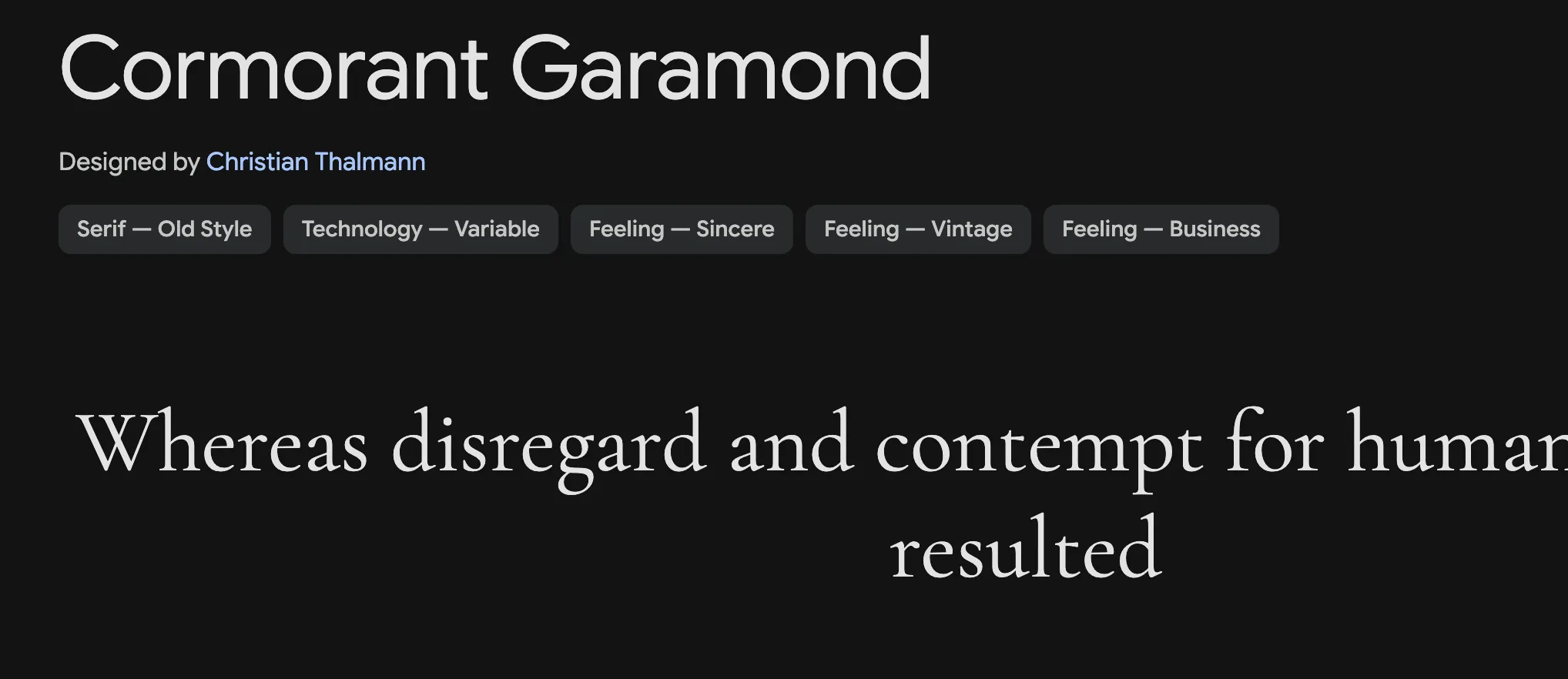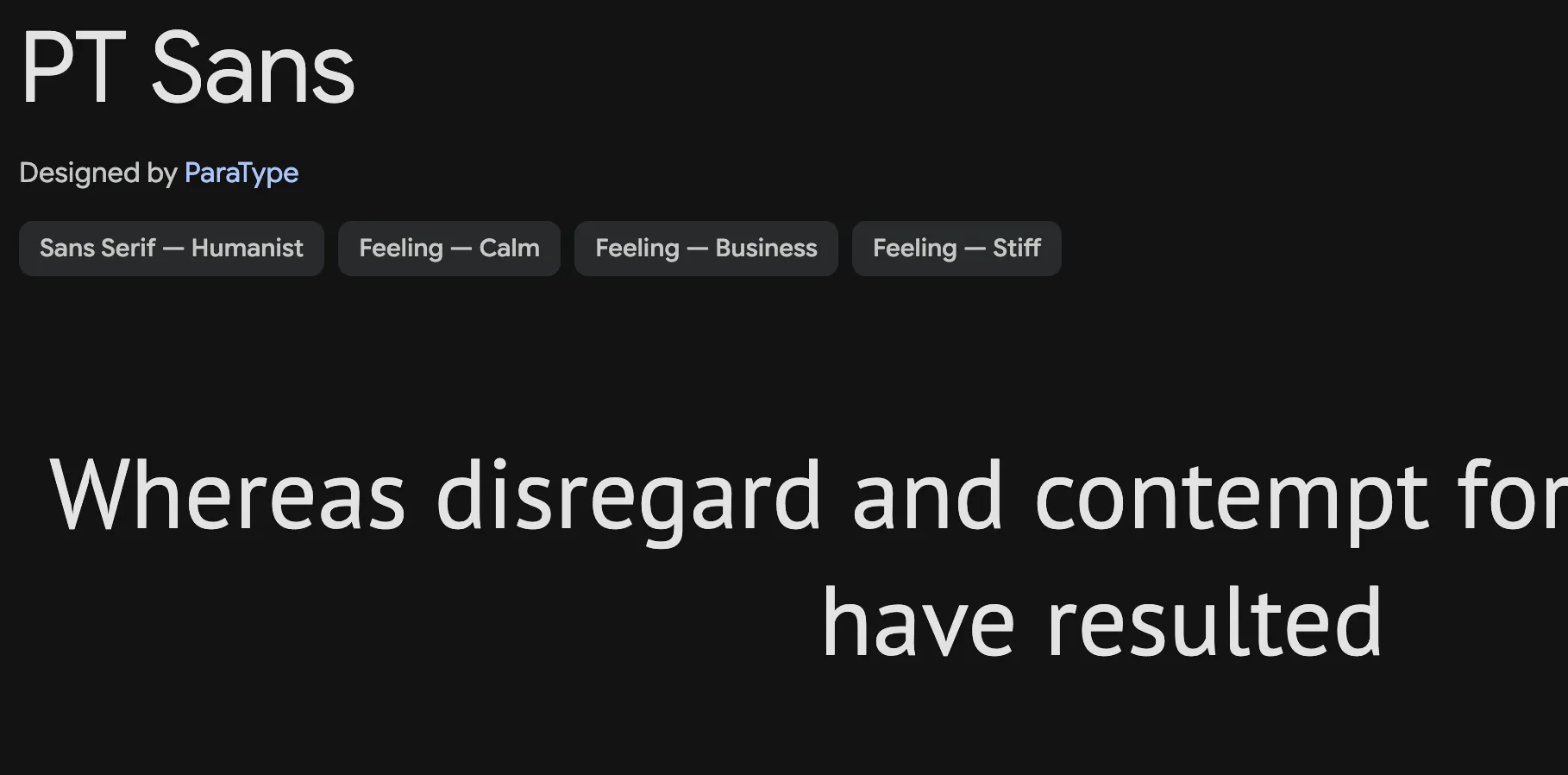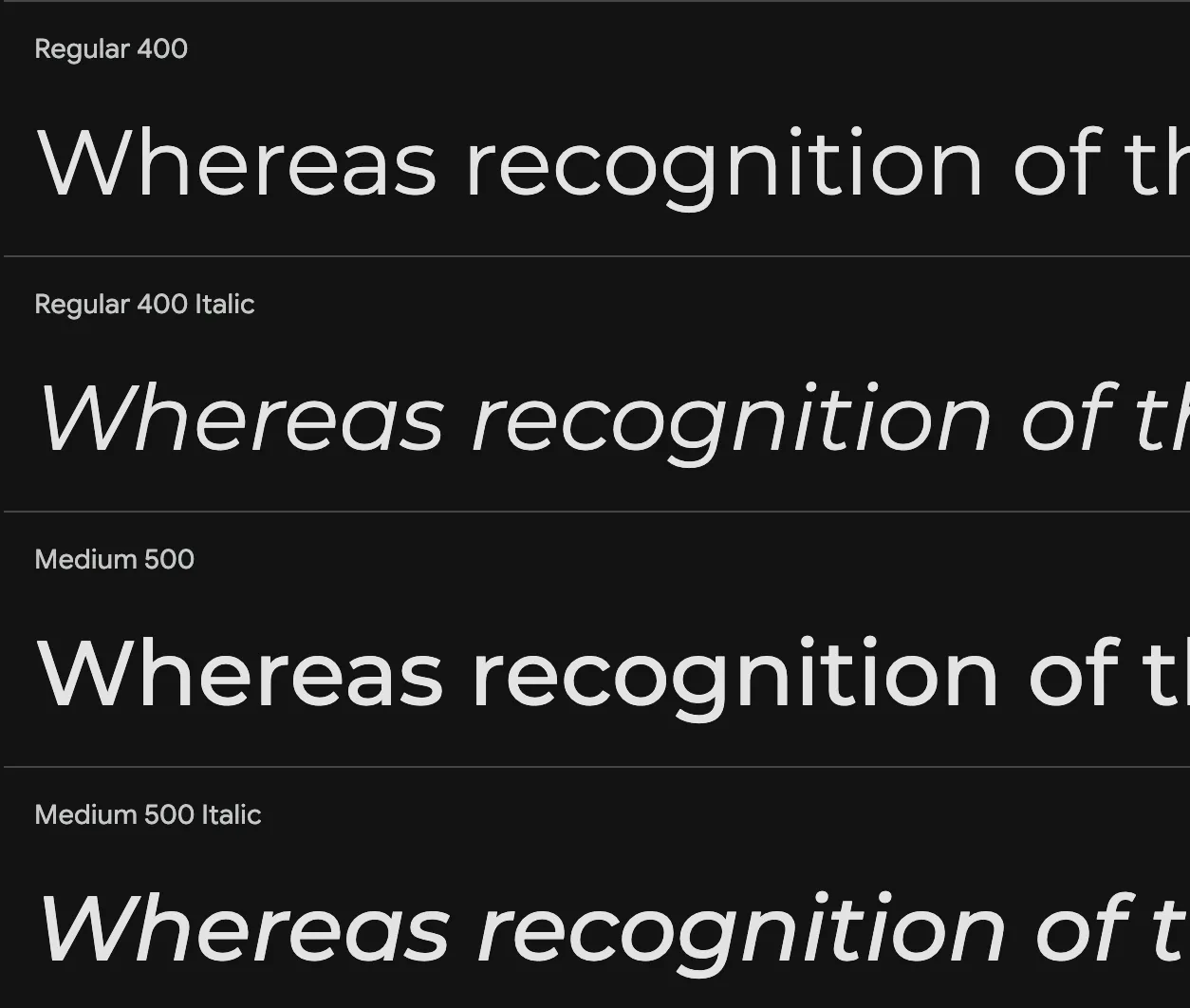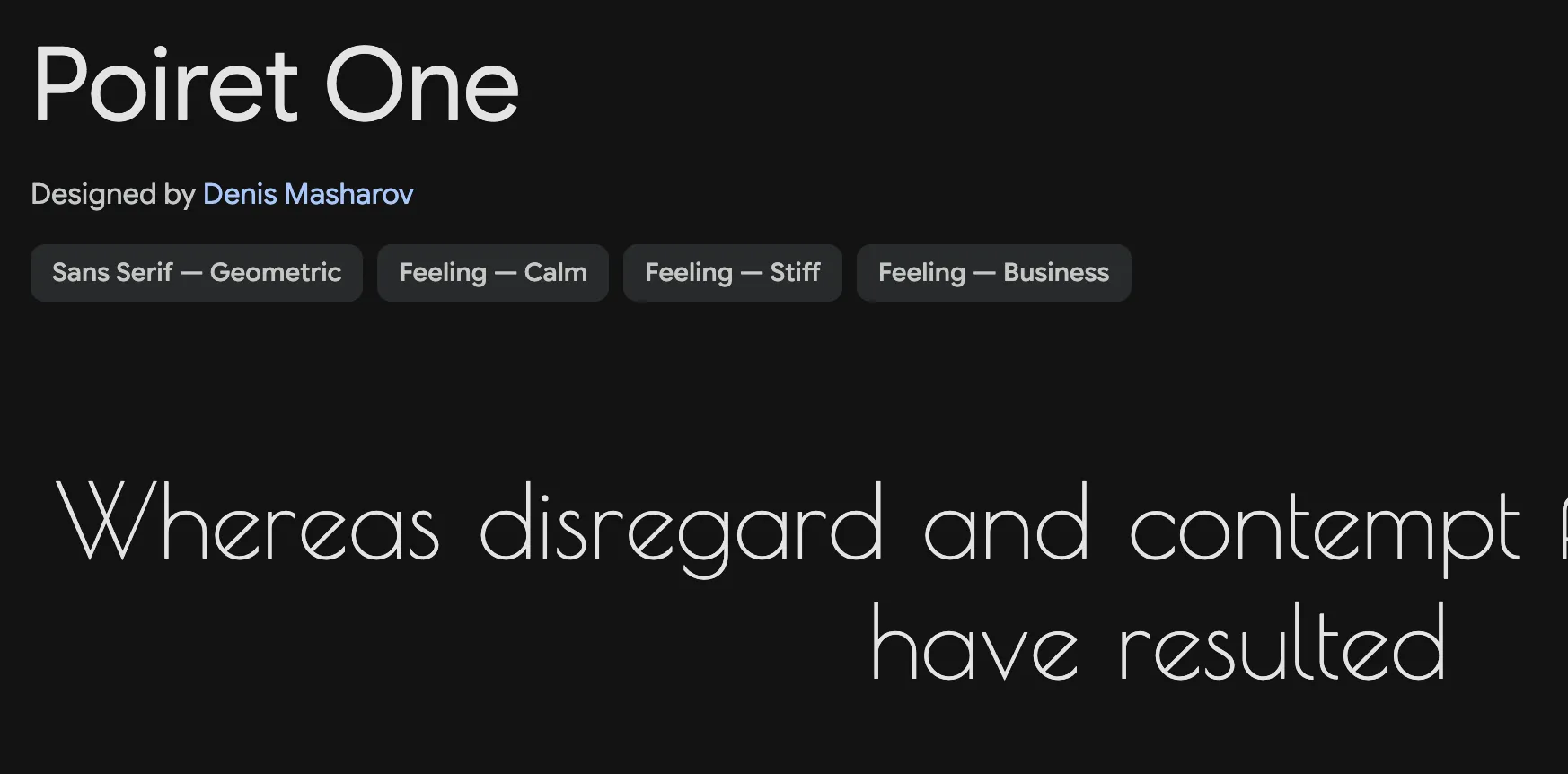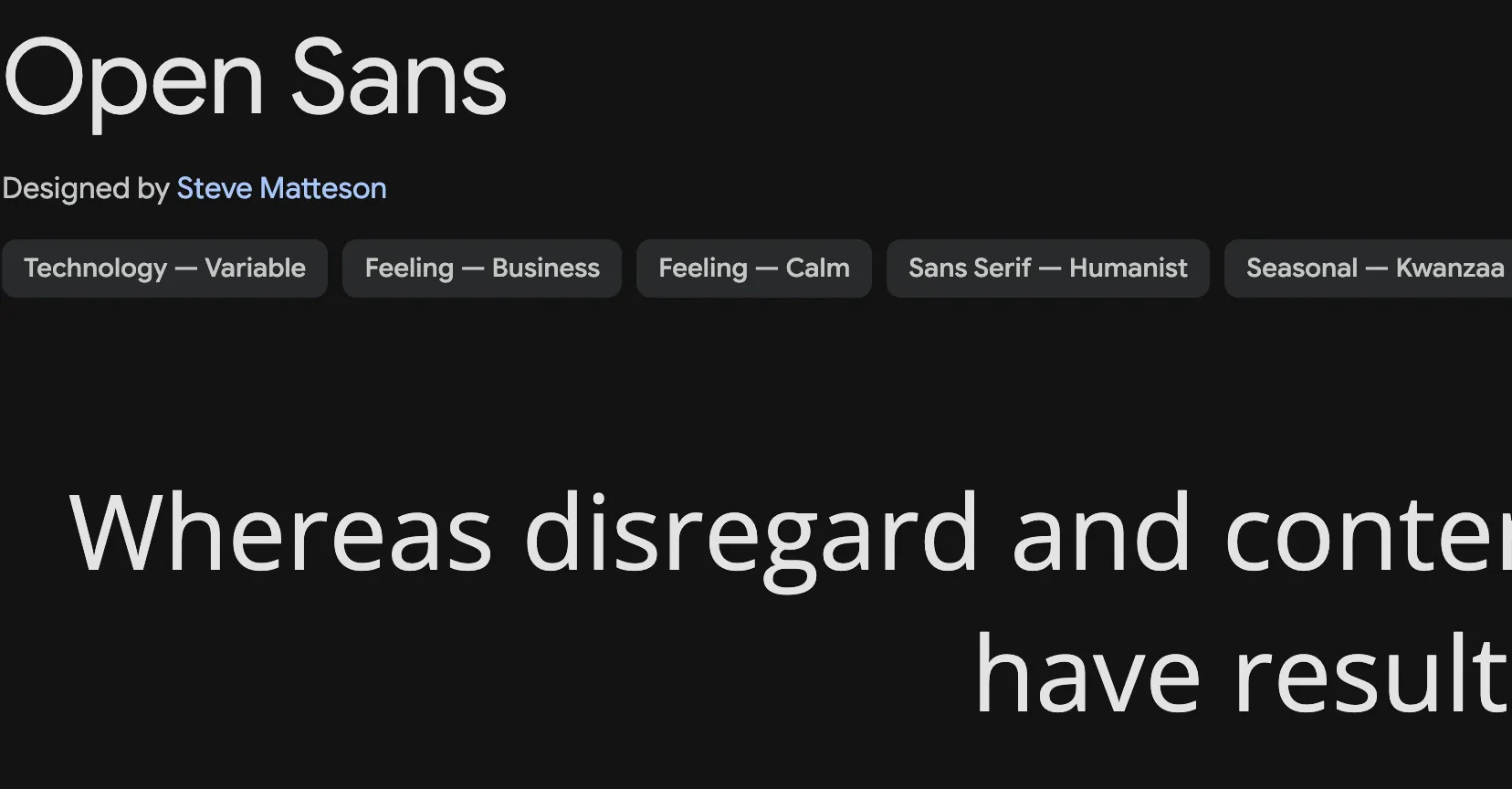
Cormorant Garamondは、Garamondの影響を受けた、優雅でクラシカルなセリフフォントです。洗練された美しさを持ち、文学的なコンテンツやアート関連のウェブサイトに最適です。上品で落ち着いた雰囲気を演出したい場合に適しています。
Sorts Mill Goudyは、伝統的で美しいセリフフォントです。Garamondに似た上品さを持ちながら、より柔らかく優しい印象を与えます。信頼感と親しみやすさを両立させたい場合に適しており、企業のウェブサイトや教育関連のコンテンツに最適です。
Poiret Oneは、独特な形状が特徴的なサンセリフフォントです。文字幅に大きな差があり、細いウェイトがおしゃれな印象を与えます。デザイン性の高いウェブサイトや、個性を表現したい場合に最適です。
Open Sansは、クセがなく、非常に読みやすいサンセリフフォントです。親しみやすい印象を与えつつ、プロフェッショナルなデザインにも適しています。本文やUIデザインに最適で、幅広い用途で利用できます。
Latoは、Open SansやHelveticaに似た、クセがなく可読性の高いサンセリフフォントです。数字も美しく、使いやすいのが特徴です。柔らかい雰囲気も持ち合わせており、幅広いデザインに適用できます。
Alluraは、流れるような美しいラインが特徴的な筆記体フォントです。エレガントで洗練された印象を与え、女性向けのウェブサイトや、ウェディング関連のデザインに最適です。見出しやロゴ、招待状などに利用すると、上品さを演出できます。
PT Sansは、ベーシックでありながら、丸みがあり優しい雰囲気を持つサンセリフフォントです。可読性が高く、本文にも適しています。親しみやすいデザインを求める場合に最適で、企業のウェブサイトやブログに適しています。
Montserratは、横長のプロポーションが特徴的なサンセリフフォントです。力強く、モダンな印象を与え、ウェブサイトでよく見かける人気のフォントです。見出しやロゴ、短いテキストに最適で、デザインに安定感をもたらします。
すっきりとした曲線が特徴で、直線が多く、スタイリッシュな印象もある丸ゴシック体フォント。等幅でクセのないデザイン。